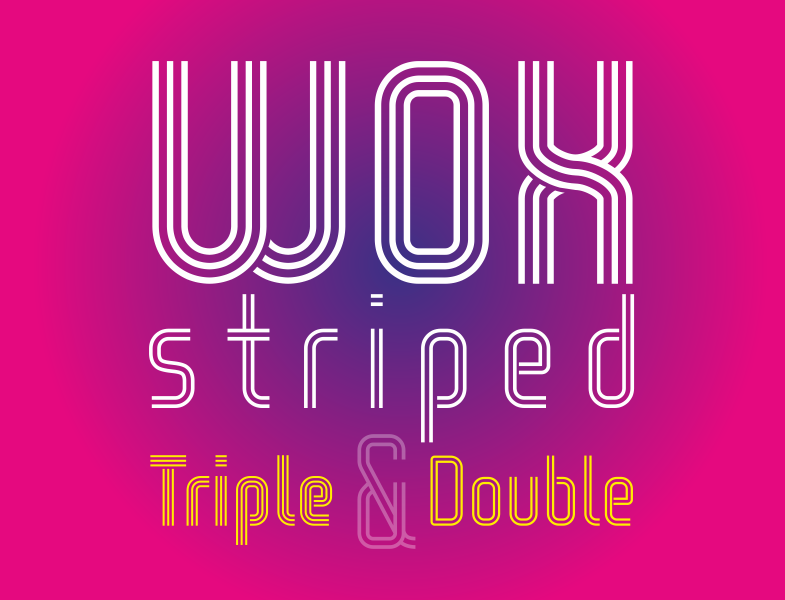
Wox Striped Font – Fonte Grátis
Wox Striped Font
A Wox Striped Font é uma opção única para designers que buscam adicionar personalidade e originalidade a suas criações digitais. Este tipo facial apresenta uma linha estilizada, perfeita para projetos de marca ou design gráfico que desejam criar um impacto visual imediato. O Studio Typo introduziu a Wox Striped Font com o objetivo de oferecer uma fonte única e versátil que se destaca dos tipos tradicionais. Suas linhas retas, curvas suaves e cores vibrantes são perfeitas para destacar textos em páginas web, aplicativos móveis ou qualquer tipo de projeto visual. Para aqueles interessados em testá-la gratuitamente, o site do Studio Typo disponibiliza uma versão limitada para teste antes da adesão à plataforma completa. Para designers e criadores de conteúdo que buscam algo diferente e interessante na sua paleta de fontes, a Wox Striped Font pode ser perfeita. Sua combinação única de linhas estilizadas e cores vibrantes faz dela uma escolha ideal para quem deseja destacar seu trabalho no meio digital.